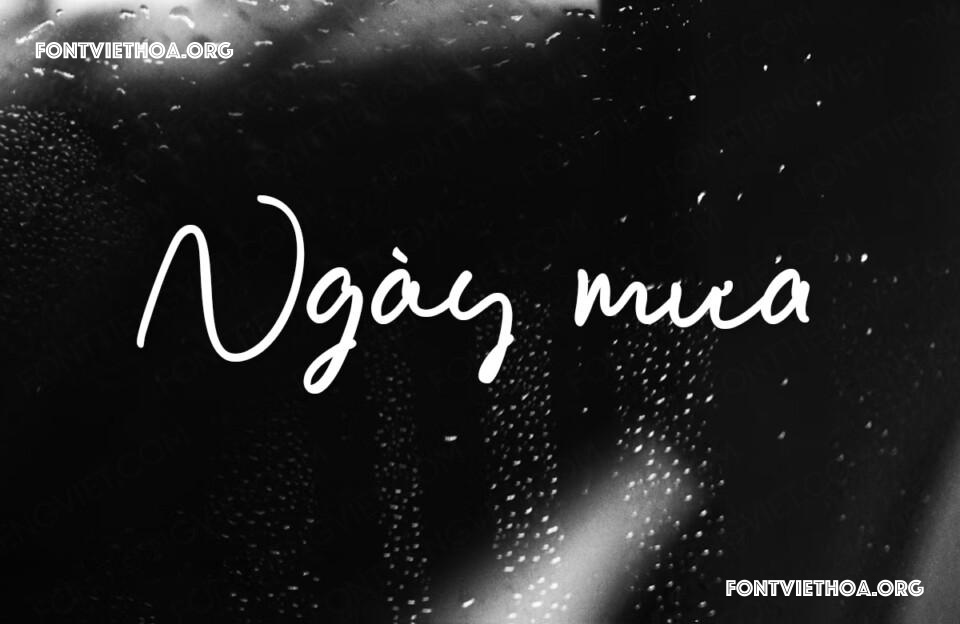
Tên font: Font Việt hóa VIP Butterfly Serenade
Tác giả: Letterhanna Type Foundry
Font Việt hóa VIP Butterfly Serenade là một font chữ viết tay độc đáo và thú vị, được thiết kế để mang lại một phong cách riêng biệt cho các thiết kế của bạn. Với những đường nét mềm mại và uyển chuyển, font này lý tưởng cho việc tạo ra những thiệp mời và thiệp cưới đẹp mắt.
Font này không chỉ giúp bạn tạo ra những thiết kế đẹp mắt mà còn giúp bạn thể hiện sự tinh tế và sang trọng. Với những tính năng đặc biệt, Font Việt hóa VIP Butterfly Serenade là sự lựa chọn hoàn hảo cho những ai muốn tạo ra những thiết kế đặc biệt.